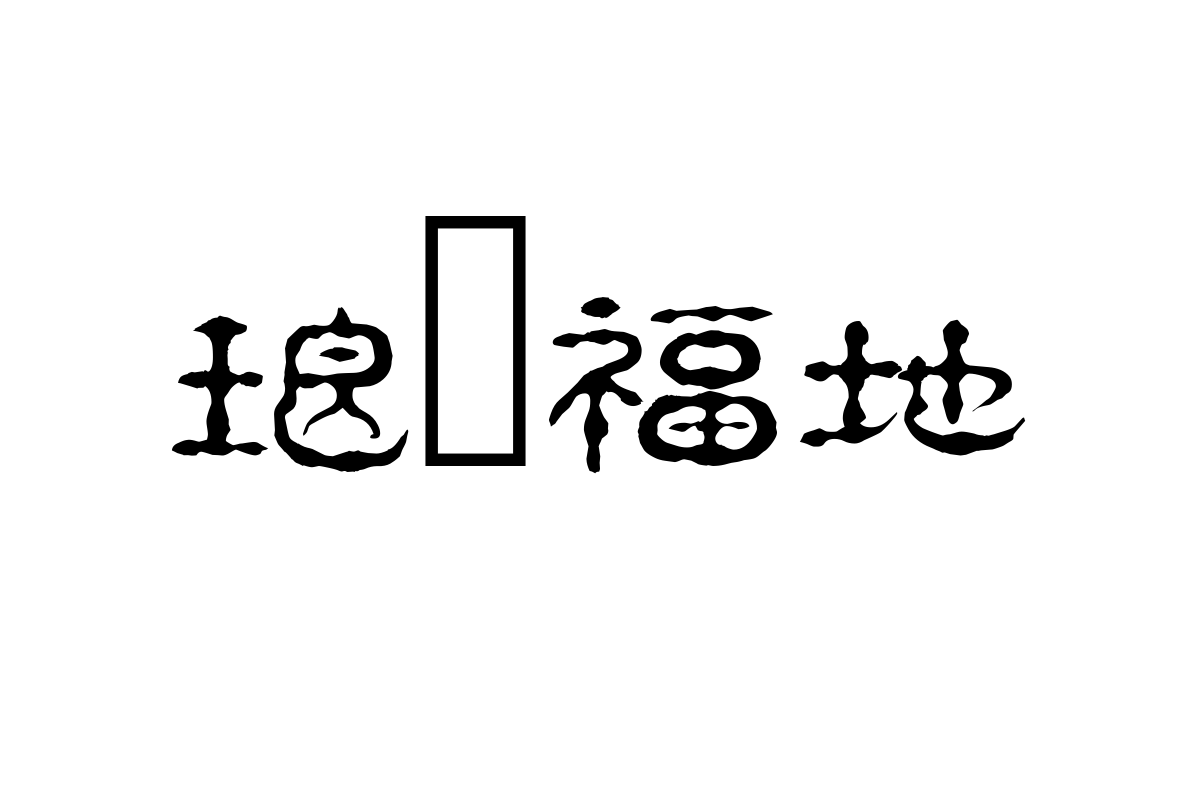
汉仪珍珠隶繁是一款现代中文字体,由汉仪字库出品。这款字体以其独特的设计和优雅的书法风格而受到欢迎。它采用了传统的隶书笔画和结构,但又加入了一些现代元素,使得字体更加时尚和易于阅读。
汉仪珍珠隶繁字体的特点包括:
1. 字形规整,线条流畅,具有很高的辨识度。
2. 适合用于标题、正文、广告、海报等各种场合。
4. 具有良好的可读性和美观性,能够提升文本的整体效果。
总的来说,汉仪珍珠隶繁是一款非常实用的中文字体,适用于多种设计场景。